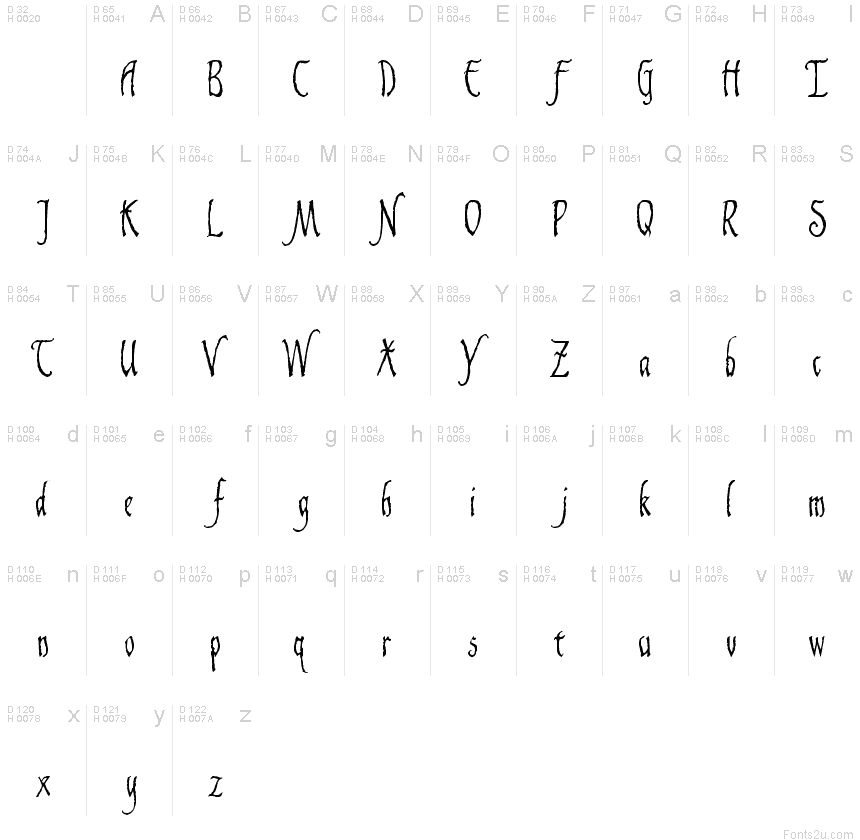
Gaiseric, di David F. Nalle, è un carattere calligrafico gratuito che sembra inciso su pergamena con una penna capricciosa. Le forme alte e irregolari e i bordi grezzi e carichi d'inchiostro le conferiscono una cruda energia medievale: un mix tra scrittura gotica e annotazioni inquietanti a margine. Ha un aspetto tattile e imperfetto nel senso migliore del termine, con tratti che ondeggiano quanto basta per apparire umani e antichi.
Con Gaiseric, puoi dare un tocco più cupo e suggestivo a copertine di libri fantasy, titoli di giochi di ruolo, loghi di band, poster a tema occulto, segnaletica per fiere medievali e interfacce di gioco. Questo font gratuito dà il meglio di sé in grandi dimensioni, dove la sua texture irregolare può davvero respirare; abbinalo a un carattere sans serif pulito e discreto per il testo principale, in modo che il carattere evocativo di Gaiseric rimanga al centro della scena.